关于宋体字小编要告诉大家一个冷知识!其实宋体字很多人常误以为是宋朝的字体,其实并不是哦!宋体字不是出现在宋朝而是出现在明朝,宋朝文化繁荣,毕昇的活字雕版印刷,让印刷业极为兴盛。明代文人仰慕宋朝文化、追捧宋刻本,便将这种字体命名为宋体字。因为宋体字阅读舒适、方正得体,字形清晰易于识别字体,迄今为止宋体字还是广泛的应用在各行各业,经过整改设计发展出多样性的宋体字,一起往下看看吧~
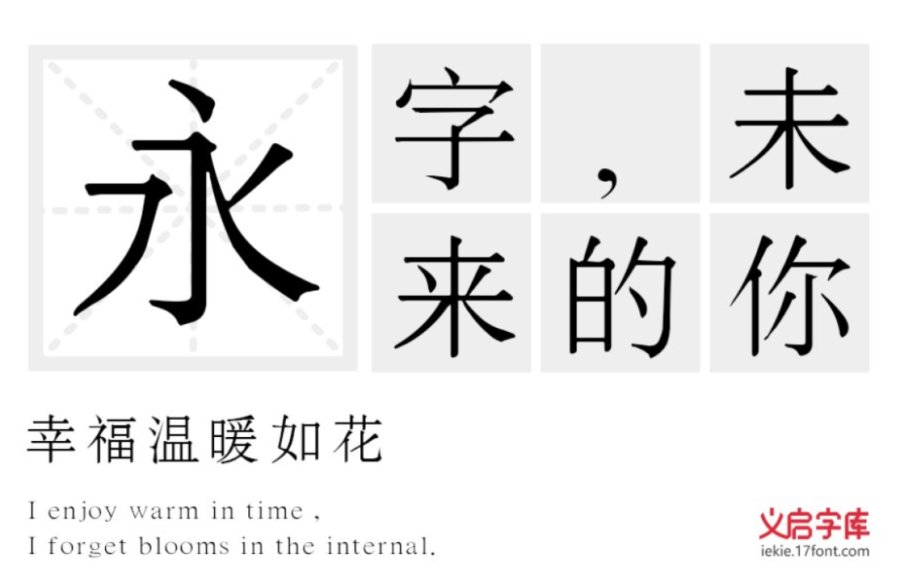
“义启新宋体”,在设计上,作者延续了宋体的特色,但宋体毕竟是为了印刷条件而发展传承的,在电子屏幕显示上村在种种弊端,而义启新宋体在继承宋体特性的基础上加大了横笔画的粗度及比例,使得显示更加优化。
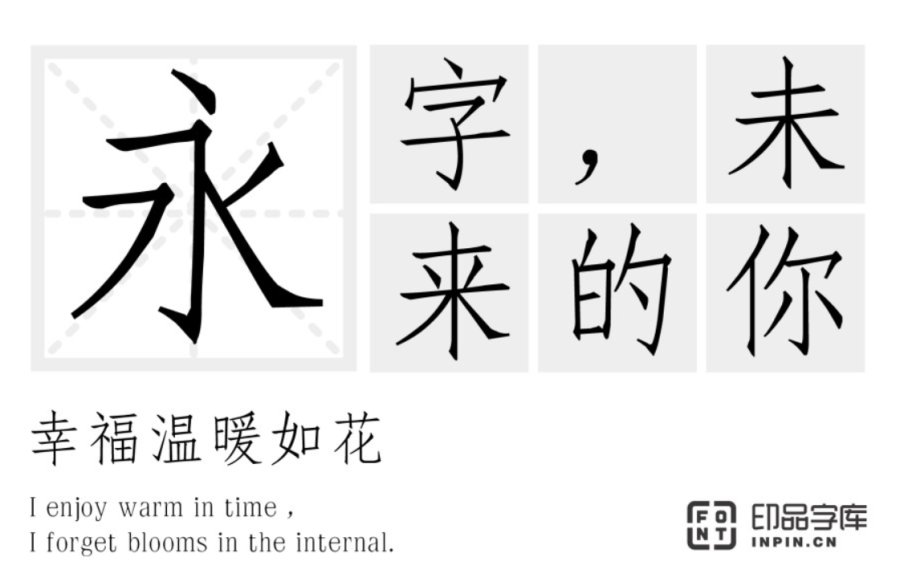
仿宋是仿照宋代的风格而制,但也不是完全仿照宋代某个文士、书法家、名人的字体。仿宋是印刷字体的一种,“印品仿宋简”是参考宋版书的雕版字体灵感创作而来,适用于排印副标题、诗词短文、批注、引文等。
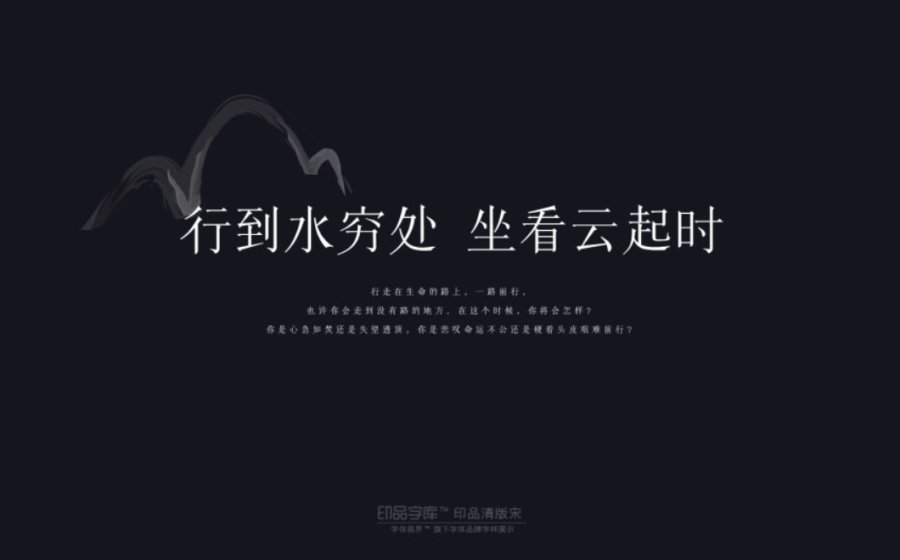
“清版宋字体”创作灵感源于清代康熙年间出版的《康熙字典》,结合清朝时期风格的宋体特点所创制的一款新宋体。字型修长、撇捺舒展、体态优雅,适合书籍与屏显阅读。
宋体字形较⽅正,基本可以同时满⾜多种排版需要,是设计师字库里必不可少的字体种类。对于设计来说合适的字体鱼儿离不开水,一款合适的之一不要任何粉饰润色也可以凭借着资深的巧妙设计使设计熠熠生辉。以上三款宋体字一定能为您的设计加分,赶快搜字体把心仪的字体下载到你的字体库里吧!